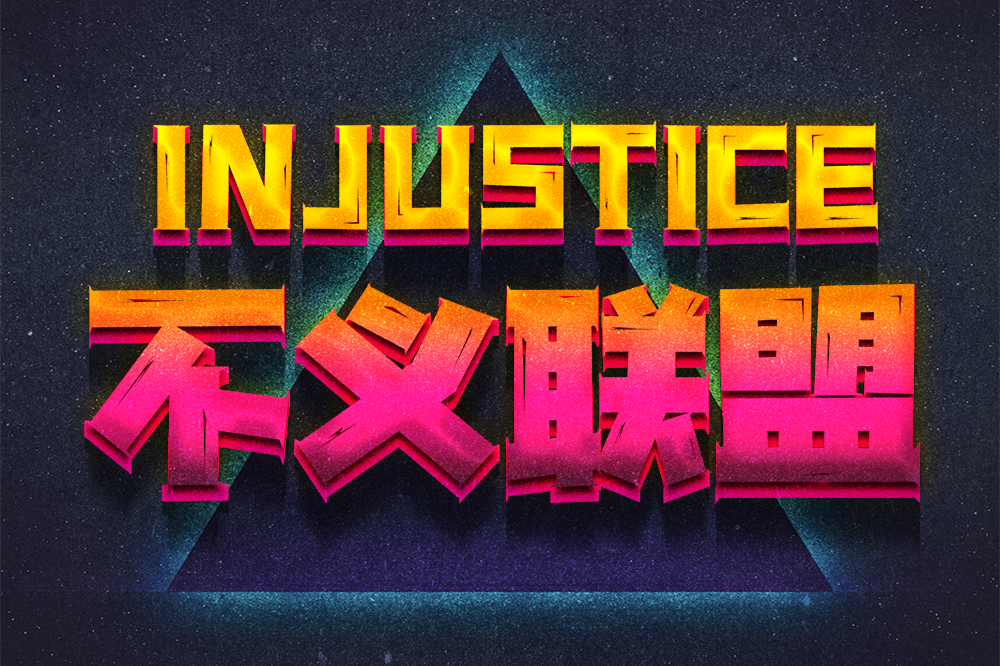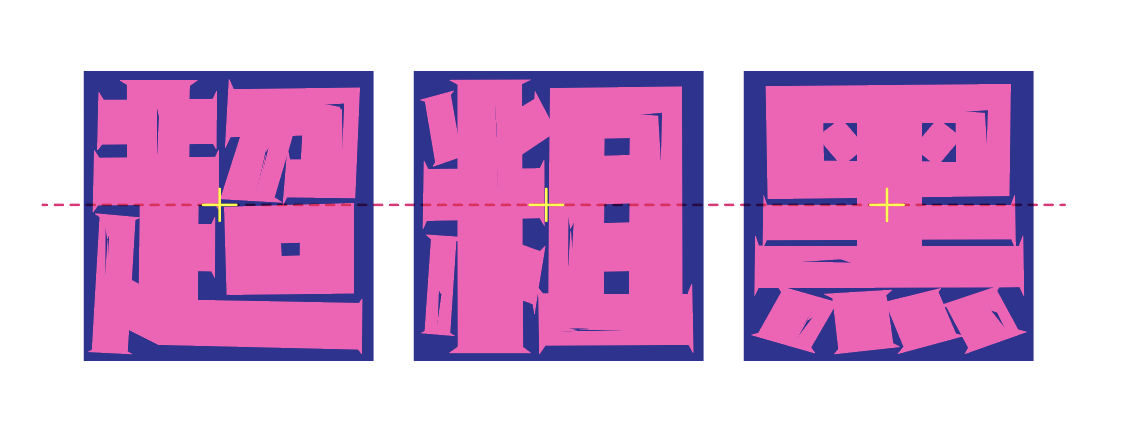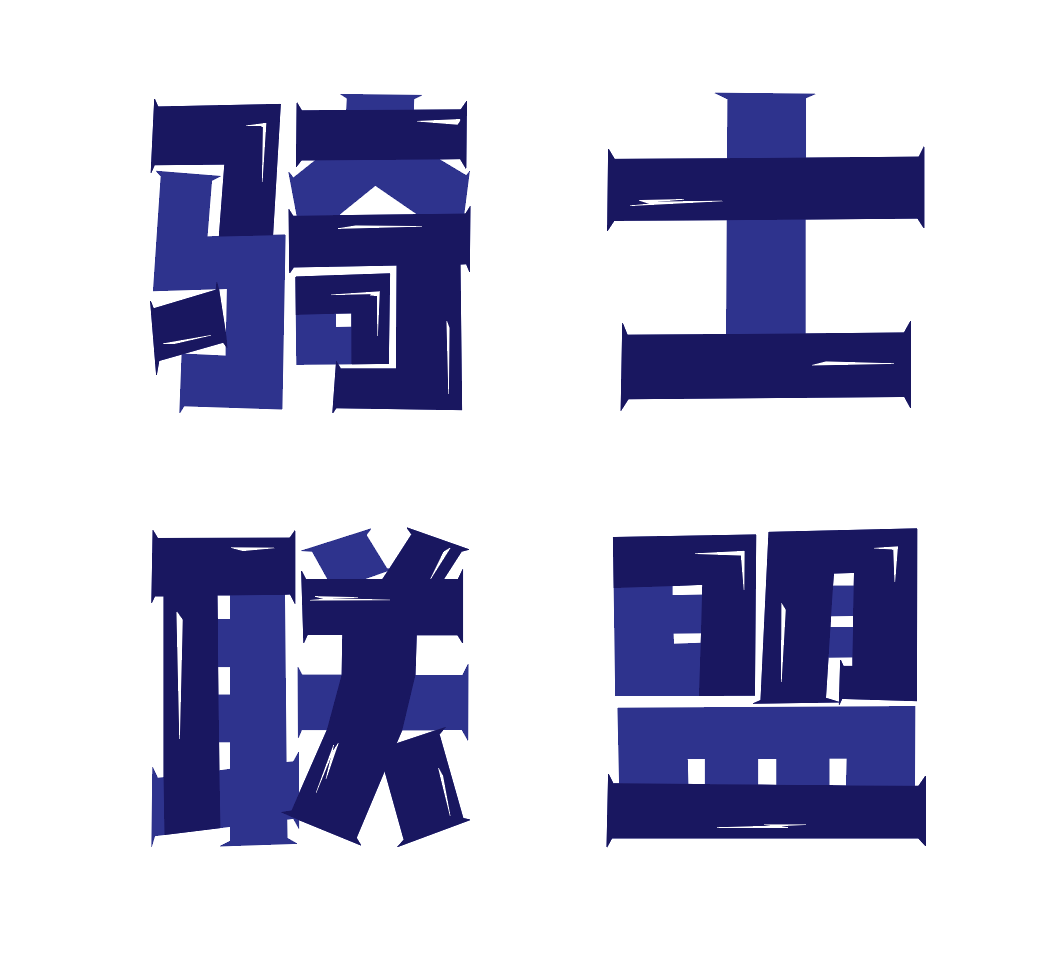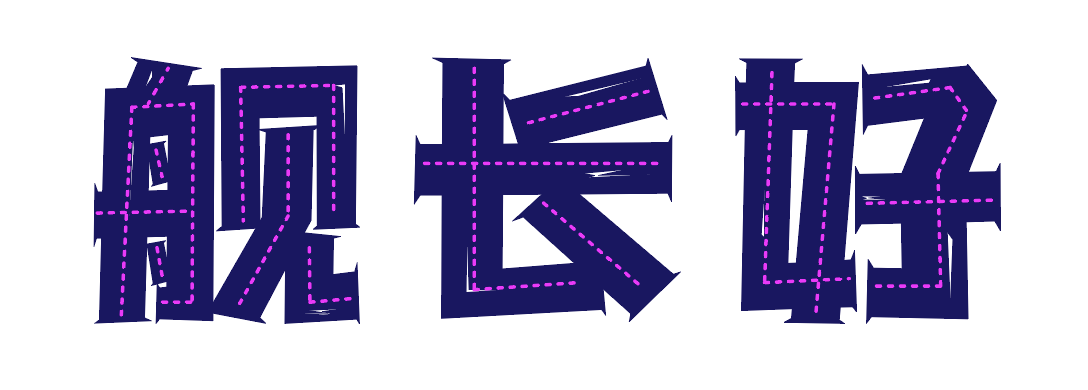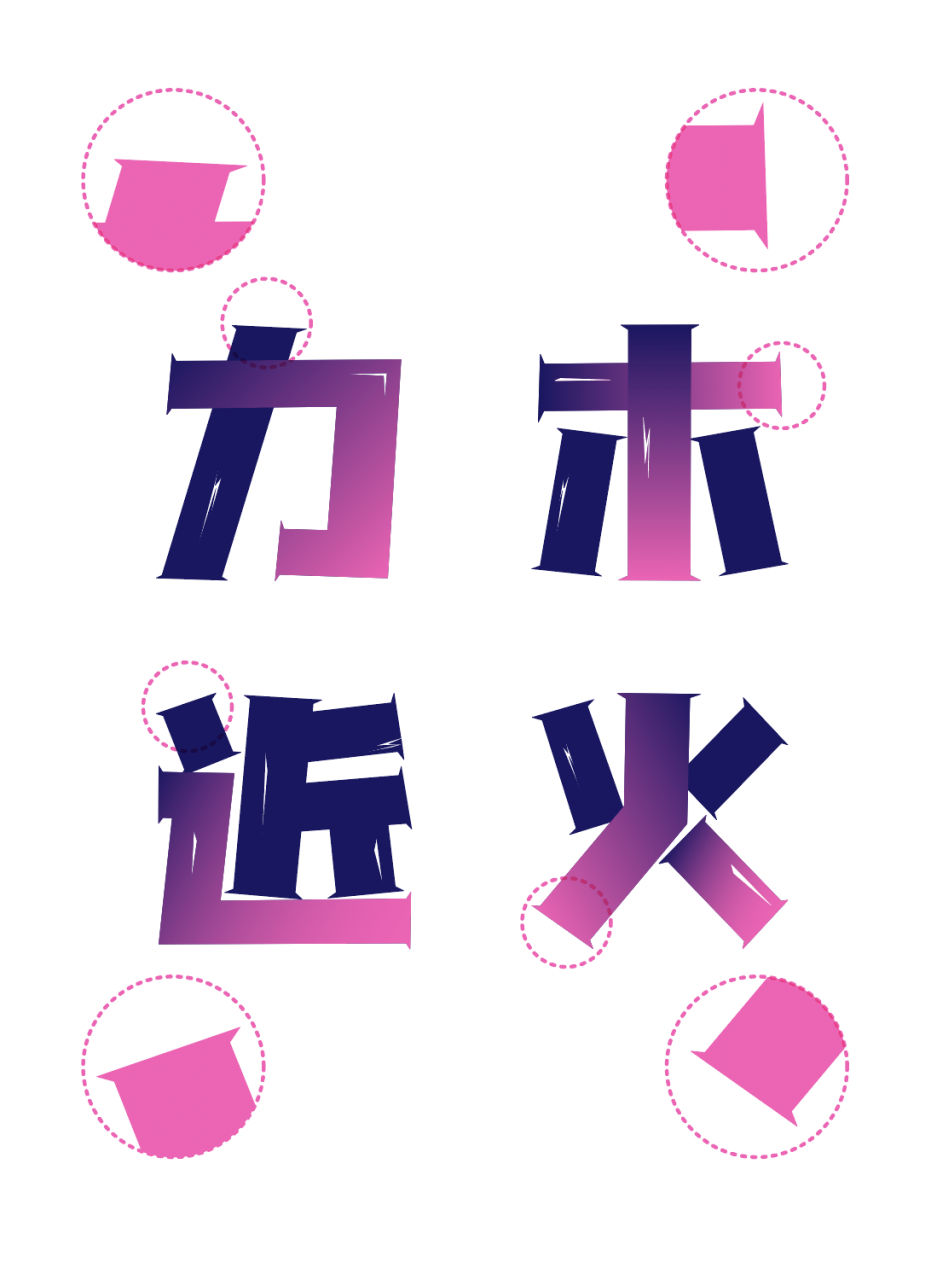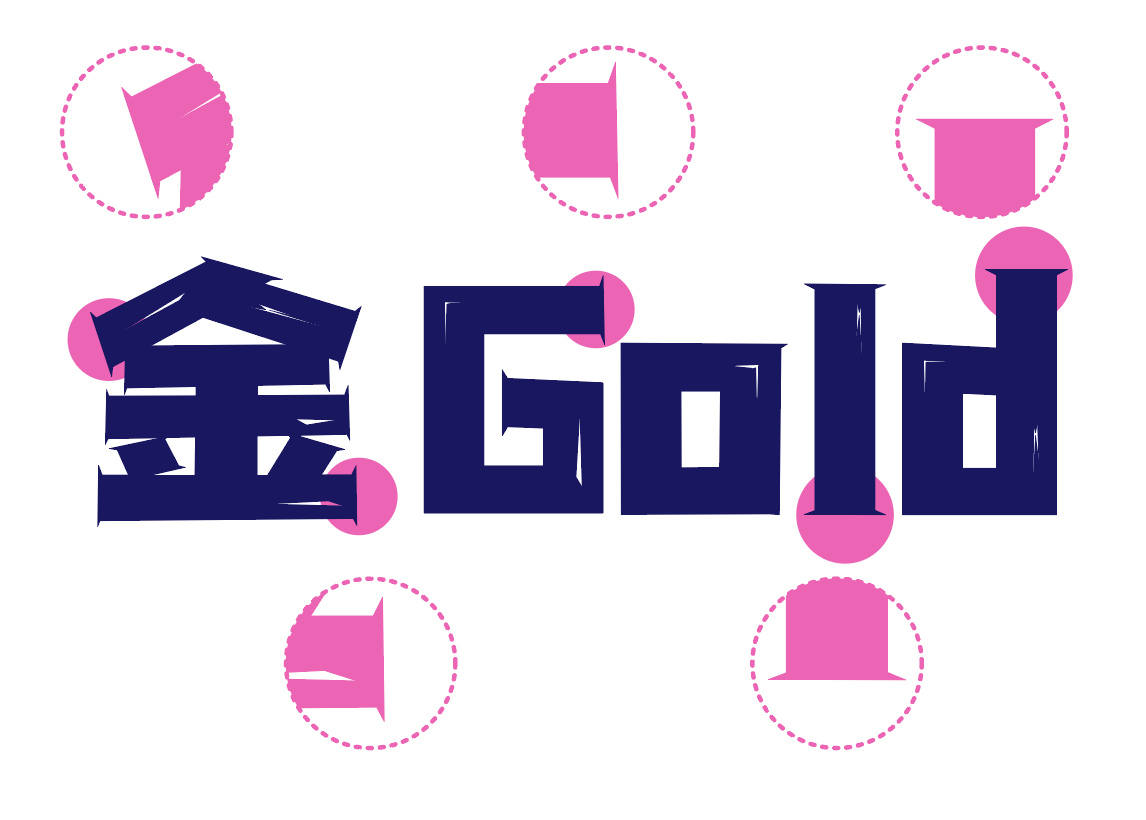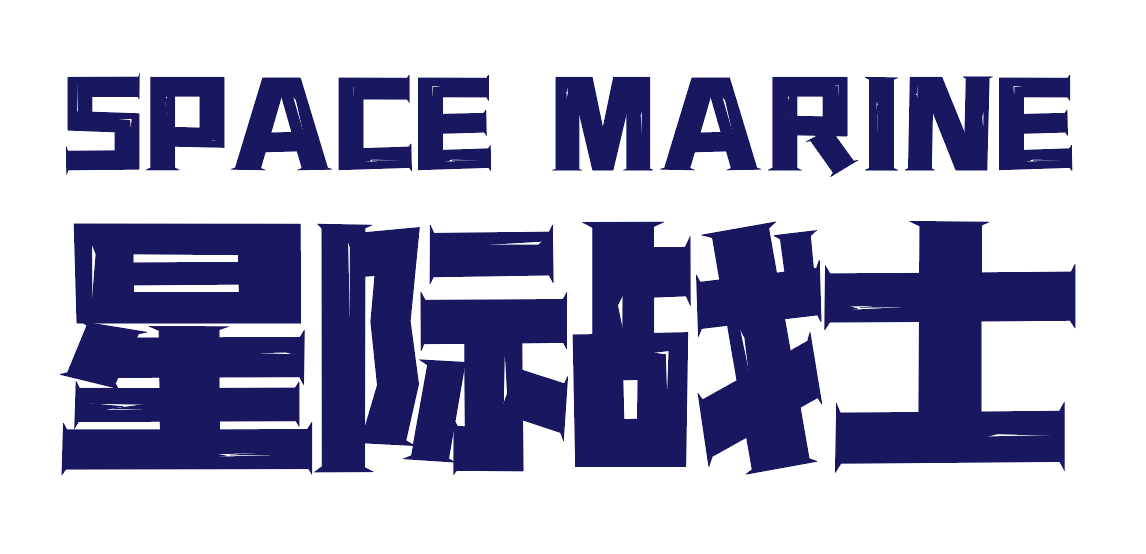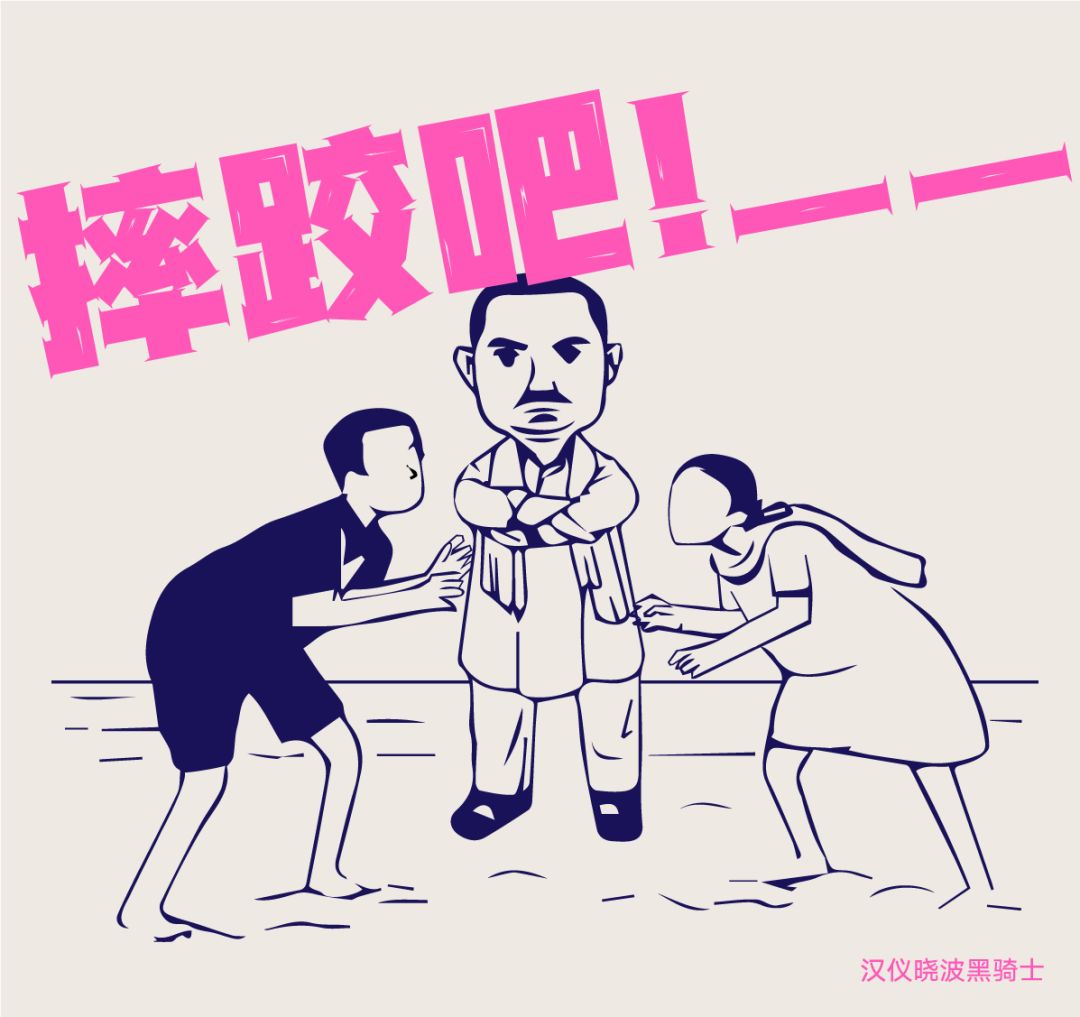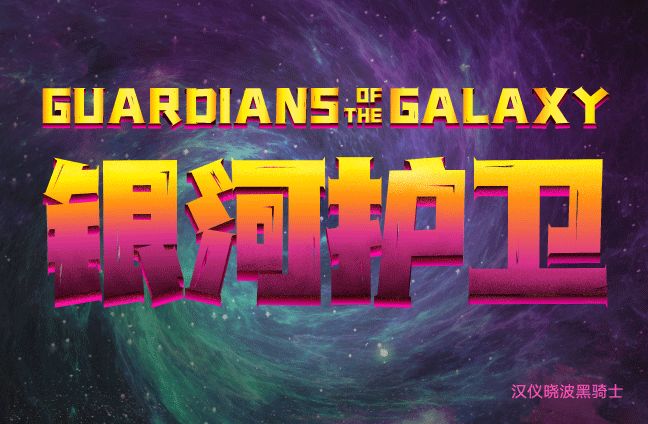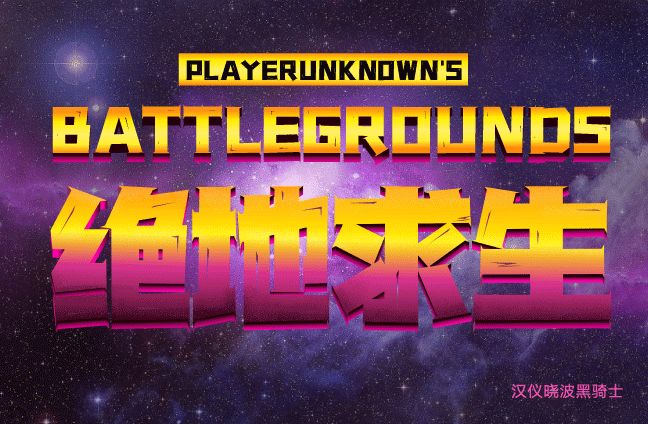
汉仪晓波黑骑士 | 一款“重金属”标题字
“汉仪晓波黑骑士”是一款具有很强装饰性的创意黑体字。它的表面有像高光一样的肌理,笔画两端带有装饰性元素,虽然字体粗钝但仍然给人一种锋利的感觉。它适合用在需要视觉冲击力的元素上,进行少量字数的标题排版设计。
汉仪晓波黑骑士 | 字形特点
“汉仪晓波黑骑士”的字符长宽比为1:1,字体重心稳定,笔画粗壮、结构布局巧妙,在版面的排版使用中,达到了醒目和冲击力强的视觉效果。
“汉仪晓波黑骑士”的表面有着锐利的特殊纹理,与笔画走向相符。使字体产生出金属般的光泽,也增加了粗体的通透感。
汉仪晓波黑骑士 | 笔画特点
“汉仪晓波黑骑士”的笔画结构里没有曲线,而是将笔画凝练为简练的几何图形,使字形更趋向于图形化处理。
“汉仪晓波黑骑士”在横、点、竖、撇、捺、钩等笔画上做了一些图形化的处理,在起笔和收笔处融入了英文衬线字体的装饰特点,做到了中西结合,这种装饰性元素使得此款字体既有稳重坚实的特点,也有活泼俏皮的感觉。
汉仪晓波黑骑士 | 中西文匹配
“汉仪晓波黑骑士”的西文字母以衬线体的风格为基础,笔画两端与中文的装饰元素相同,形成了具有独特风格的西文字母。
“汉仪晓波黑骑士”西文字母的表面同样具有“高光”纹理,中西文搭配使用时十分和谐统一。
汉仪晓波黑骑士 | 应用效果